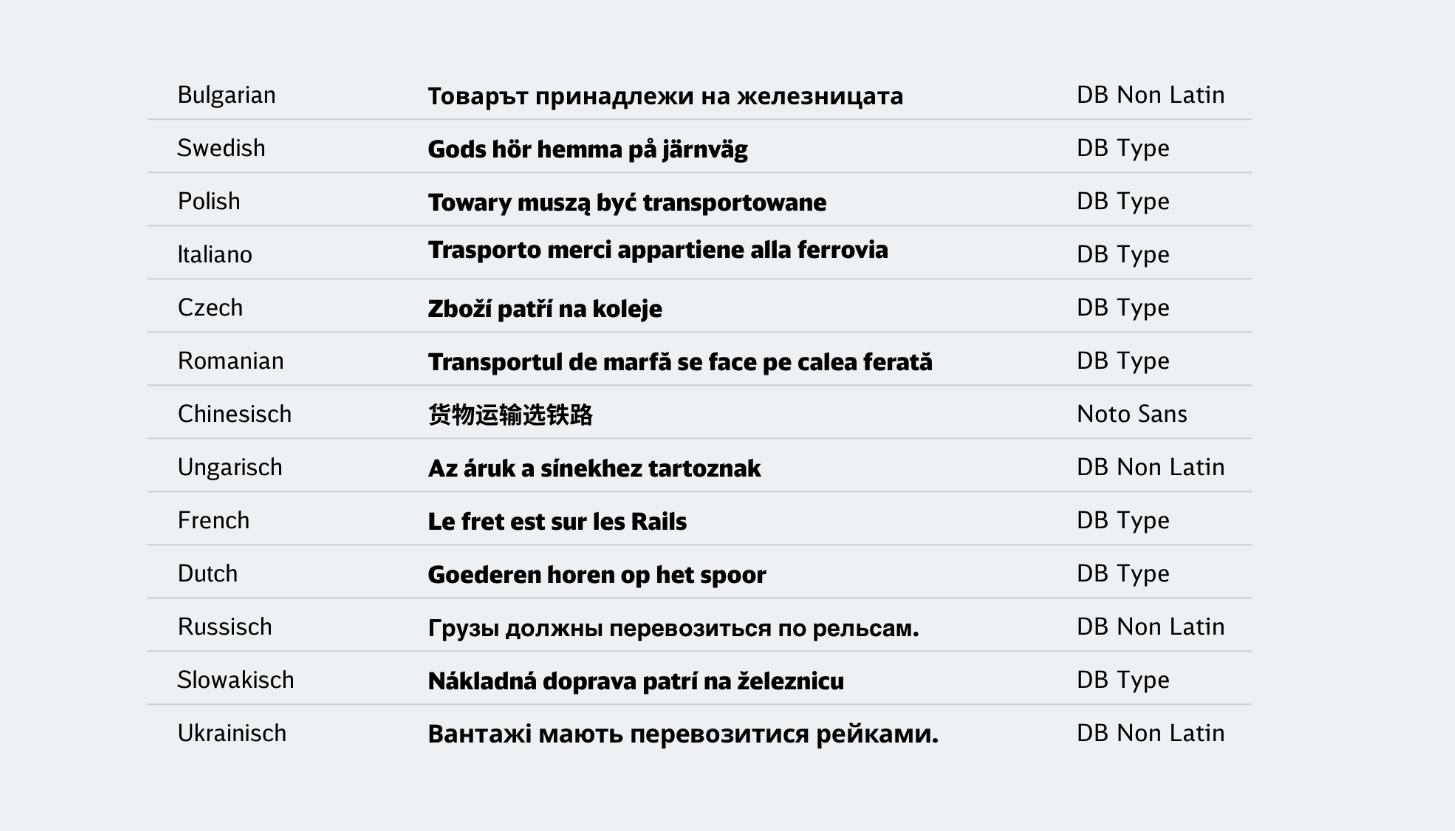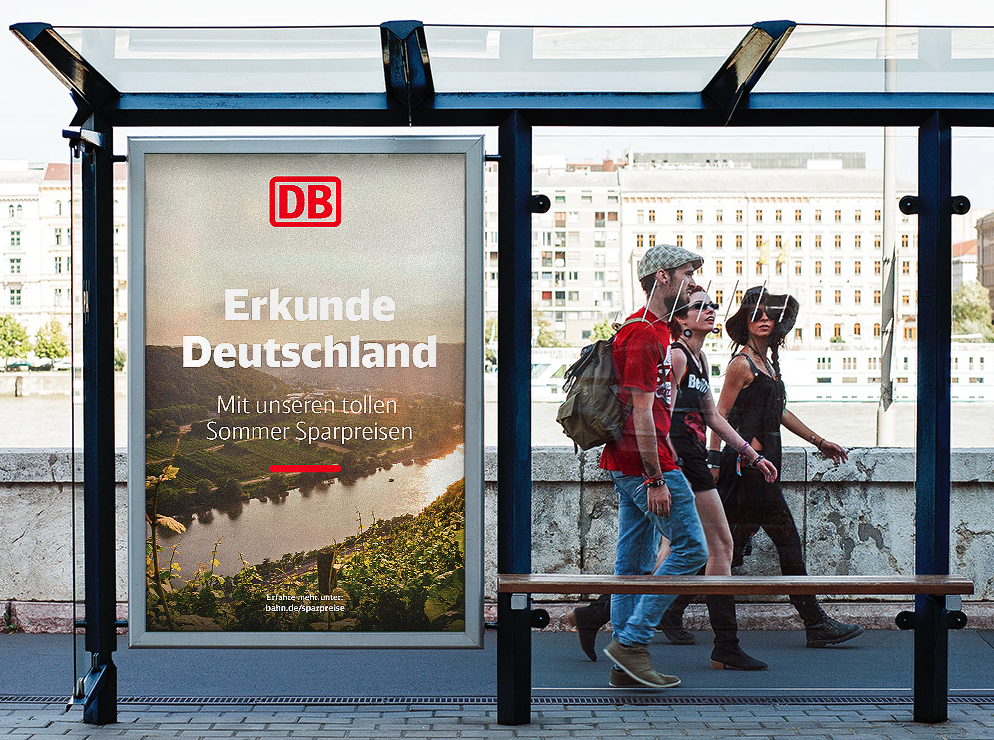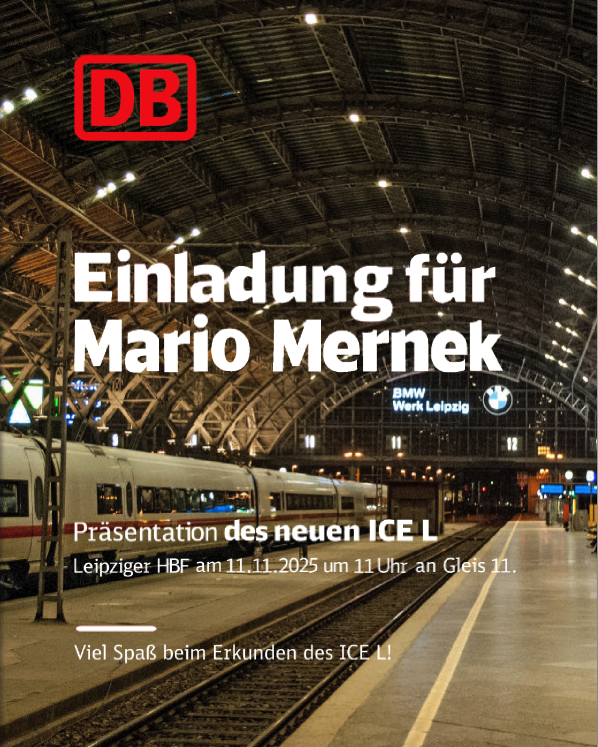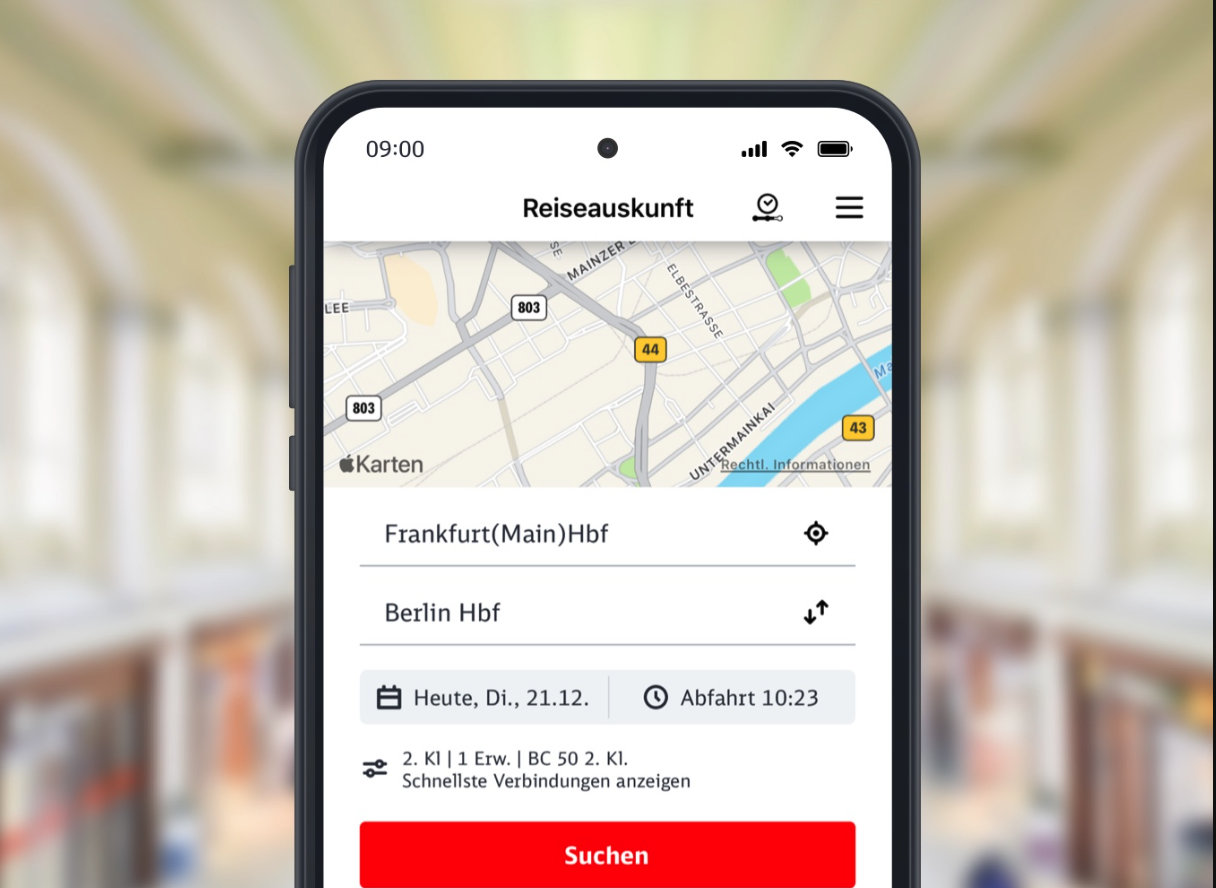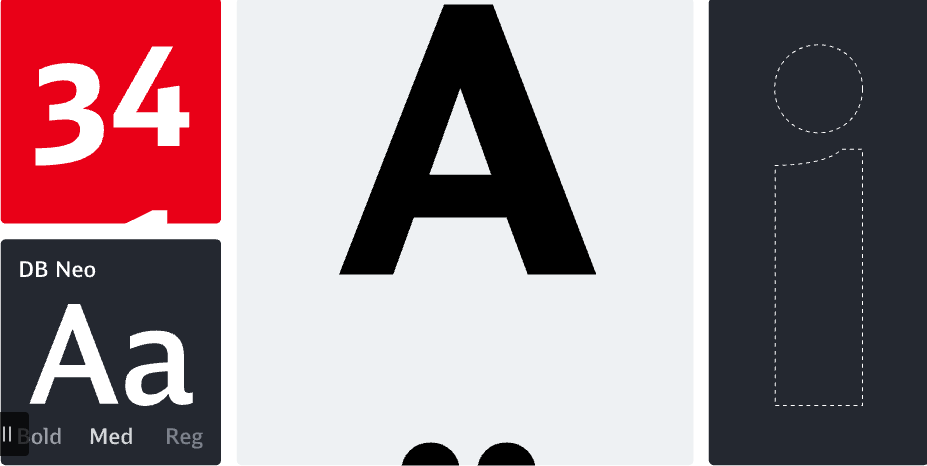
DB Neo – eine Schrift für alle Fälle.
Die DB Type, unsere ikonische Markenschrift, hat ein technisches Upgrade bekommen. Unser neuer Standard mit neuem Namen im bewährten Look. Die komplett modernisierte und optimierte DB Neo ist kostenfrei für alle Anwender*innen und bereits vorinstalliert . Der neue Name hilft dabei, die alte Font verwechslungsfrei auszutauschen. Keine Sorge: DB Head und DB Sans können einfach ersetzt werden, ohne dass sich bestehende Layouts dadurch ändern.
Die Anlässe und Medien, in denen wir unsere Hausschrift einsetzen, sind so vielfältig wie unser Konzern. Aus diesem Grund haben wir mit der DB Type ein umfangreiches Schriftsystem, das diverse Schriftfamilien umfasst. DB Neo, DB Neo Screen und DB Neo Office. Was sie alle eint: eine zugängliche Anmutung, hohe Funktionalität und Eigenständigkeit. Die FAQ am Ende dieser Seite beantworten die wichtigsten Fragen zur DB Type, der Lizensierung sowie dem Einsatz.
DB Neo – Modernisiert, optimiert, vereinfacht – eine Schrift für alle Fälle
Die DB Type, unsere ikonische Markenschrift, hat ein technisches Upgrade bekommen. Unser neuer Standard mit neuem Namen im bewährten Look. Die komplett modernisierte und optimierte DB Neo ist kostenfrei für alle Anwender*innen und bereits vorinstalliert . Der neue Name hilft dabei, die alte Font verwechslungsfrei auszutauschen. Keine Sorge: DB Head und DB Sans können einfach ersetzt werden, ohne dass sich bestehende Layouts dadurch ändern.
Sprachräume.
Die DB Type unterstützt lateinische Schriften, wie sie in Westeuropa, Amerika und Australien weit verbreitet sind. Bei Sprachen, die keine lateinische Zeichen verwenden, kommt die DB Non Latin zum Einsatz. Stelle dabei sicher, dass du die Lizenzbestimmungen für die DB Non Latin berücksichtigst.
Vorgaben für einen einheitlichen Gebrauch.
- Nutze den BULLET GID: 116 mit dem Unicode: 2022, der DB Neo Sans Glyphen in DB Red 500.
- er Erstzeileneinzug entspricht ca. 1 Ausgleich-Leerzeichen.
- Der Abstand der Bullet Points zum Text entspricht dem Wert des Halbgeviertstrich.
- Eingerückte Bullet Points sind stets bündig mit dem Text der darüberliegenden Aufzählungsebene.
Einfach stark, wie die DB Type über die Jahre gereift ist. Die neue DB Neo Screen zeigt perfekt, wie man Lesbarkeit auf kleinen Displays mit Markenidentität verbindet. Spiekermanns Erbe wird hier würdig weitergeführt!"